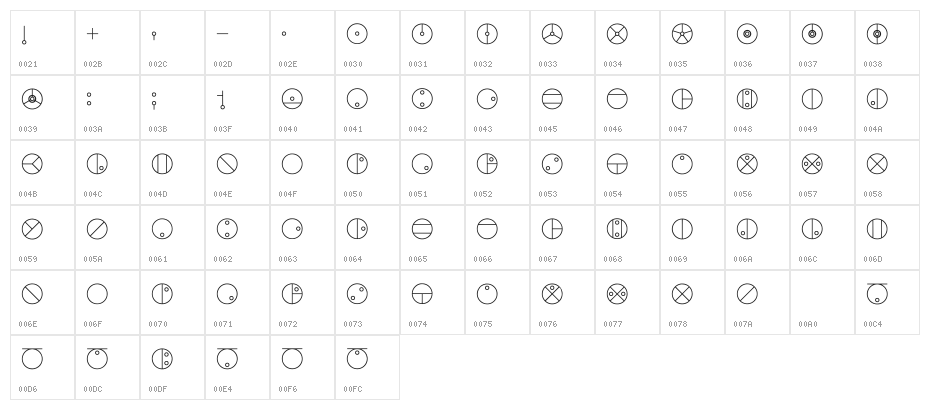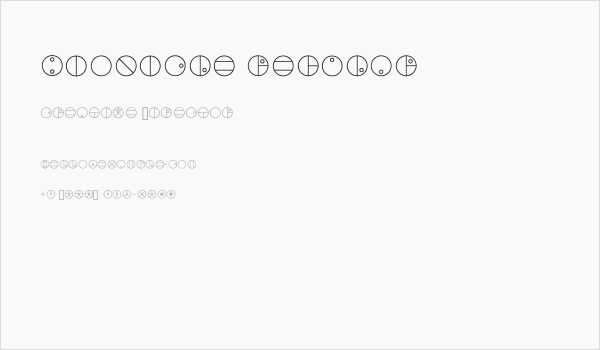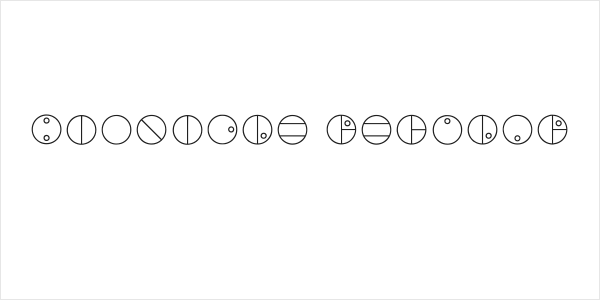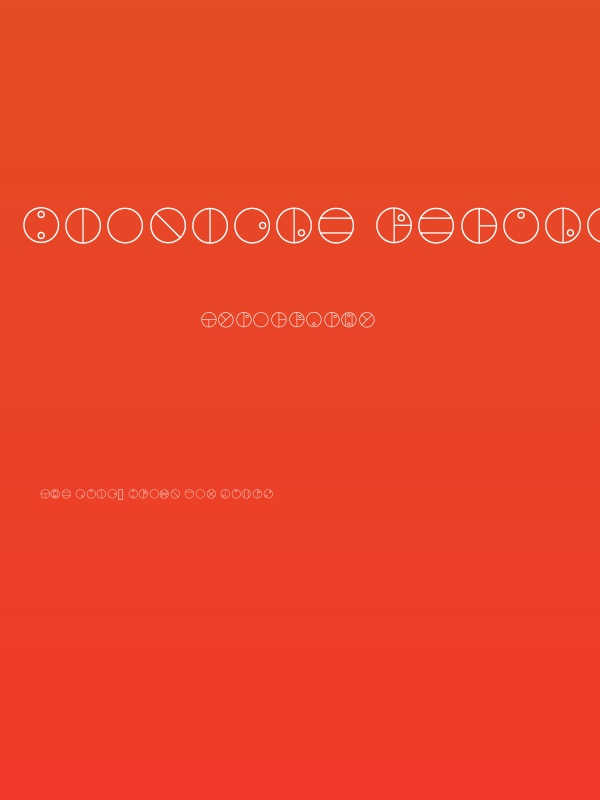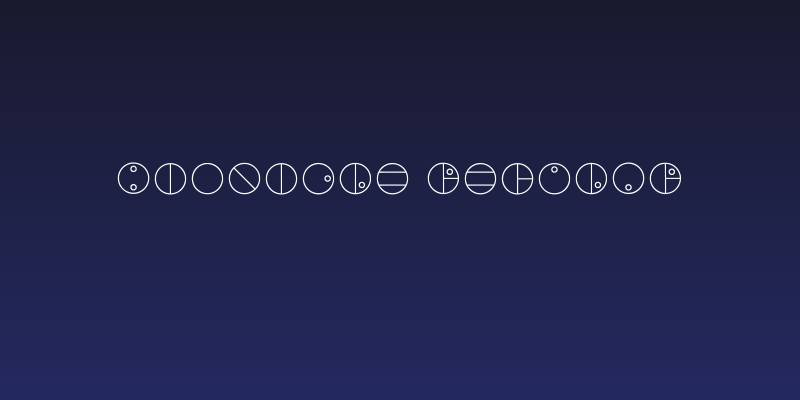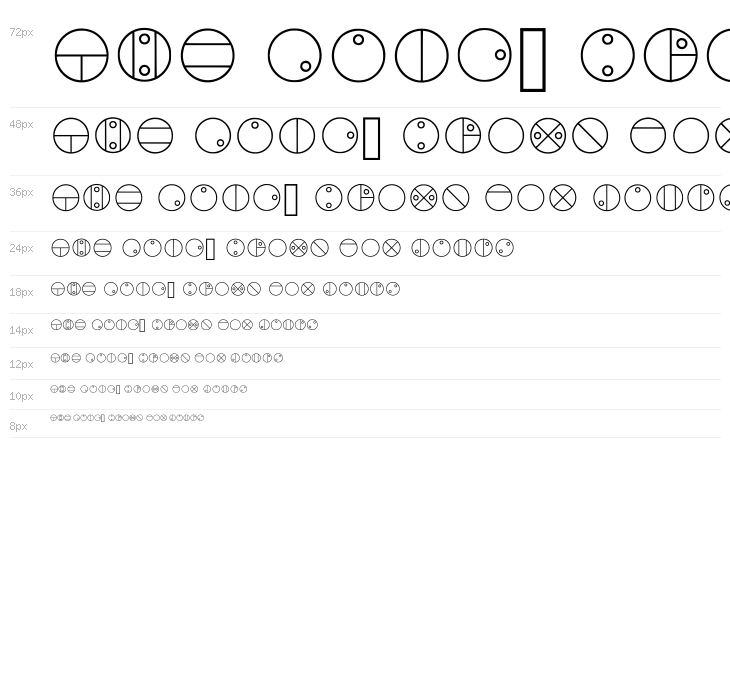
Bionicle Regular Font
| Stil general | Futuristic, Abstract |
| Caz de utilizare | Logos, Posters, Creative projects |
| Proiecte propuse | Ideal for sci-fi themed designs, video game interfaces, futuristic branding, and creative posters. |